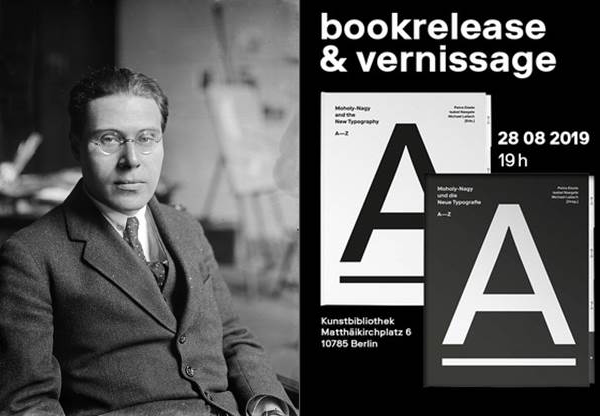
László Moholy-Nagy und die Neue Typografie – Rekonstruktion einer Ausstellung Berlin 1929
Eine Ausstellung der Kunstbibliothek – Staatliche Museen zu Berlin in Kooperation mit dem Institut Designlabor Gutenberg der Hochschule Mainz
Im Jahr 1929 wagte die Kunstbibliothek mit der Ausstellung »Neue Typographie« im Martin Gropius-Bau den Blick auf die Zukunft der Schriftkommunikation. Im Mittelpunkt: der programmatische Ausstellungsraum »Wohin geht die typographische Entwicklung« des Bauhaus-Künstlers Laszlo Moholy-Nagy. Neunzig Jahre später – im Bauhaus-Jubiläumsjahr – wird dieser Raum erstmals rekonstruiert.
Die Ausstellung ist vom 29. August bis zum 15. September 2019 im Ausstellungsraum der Kunstbibliothek am Kulturforum zu sehen.